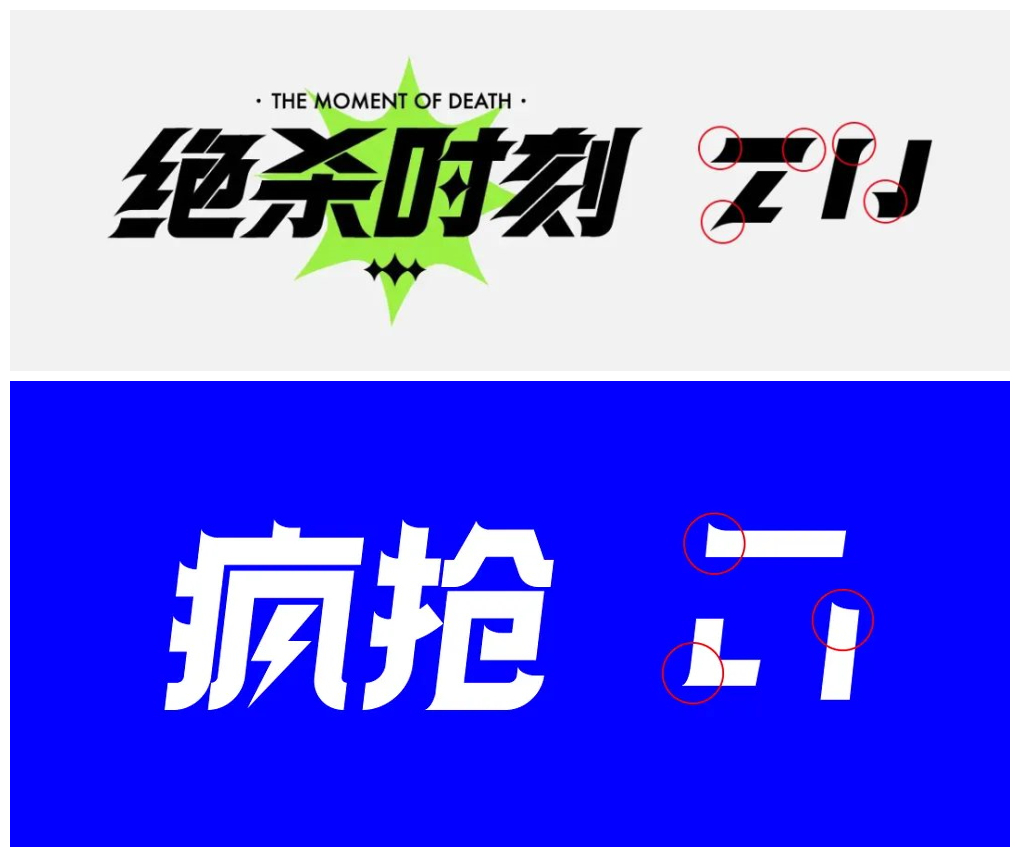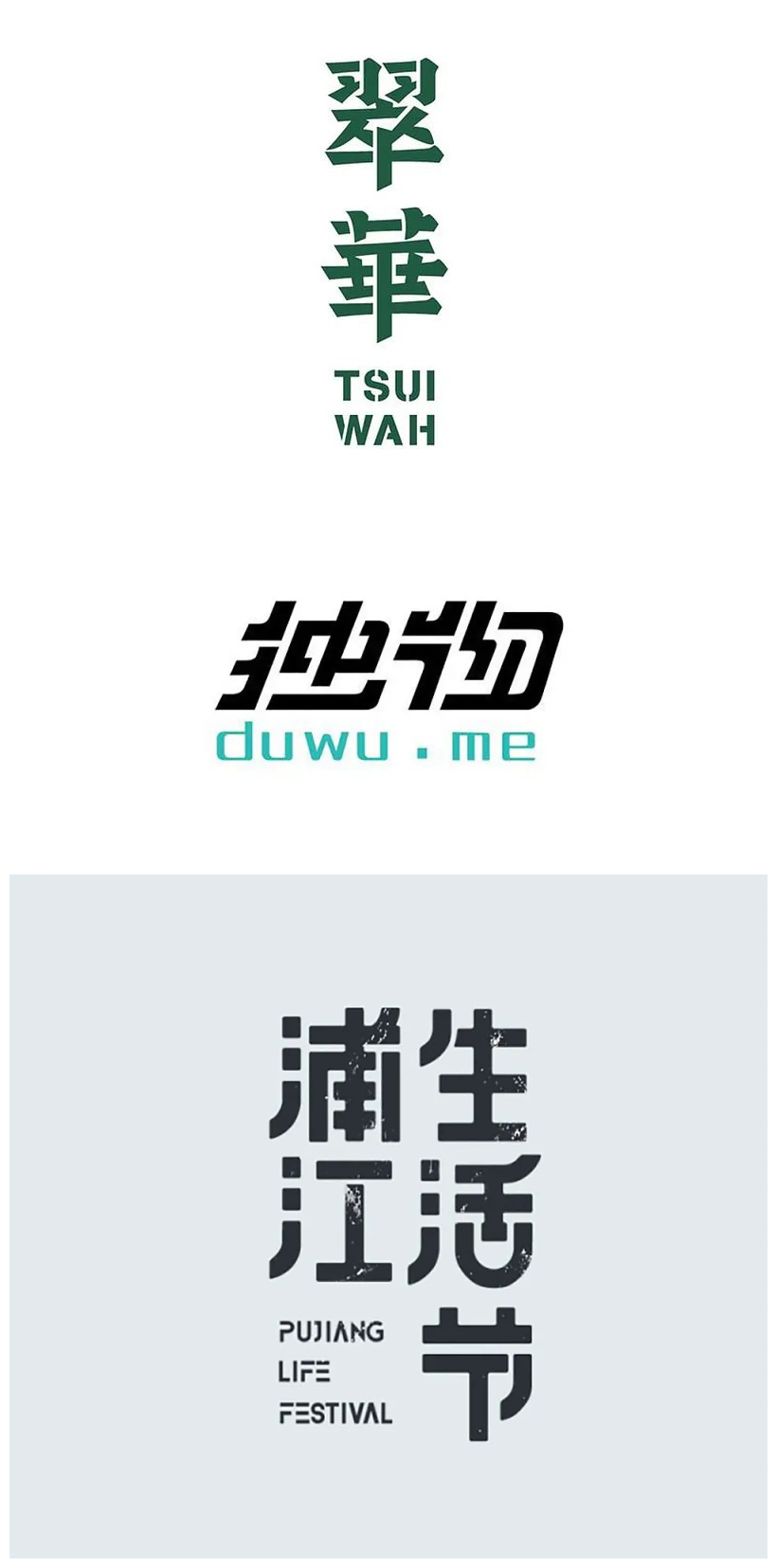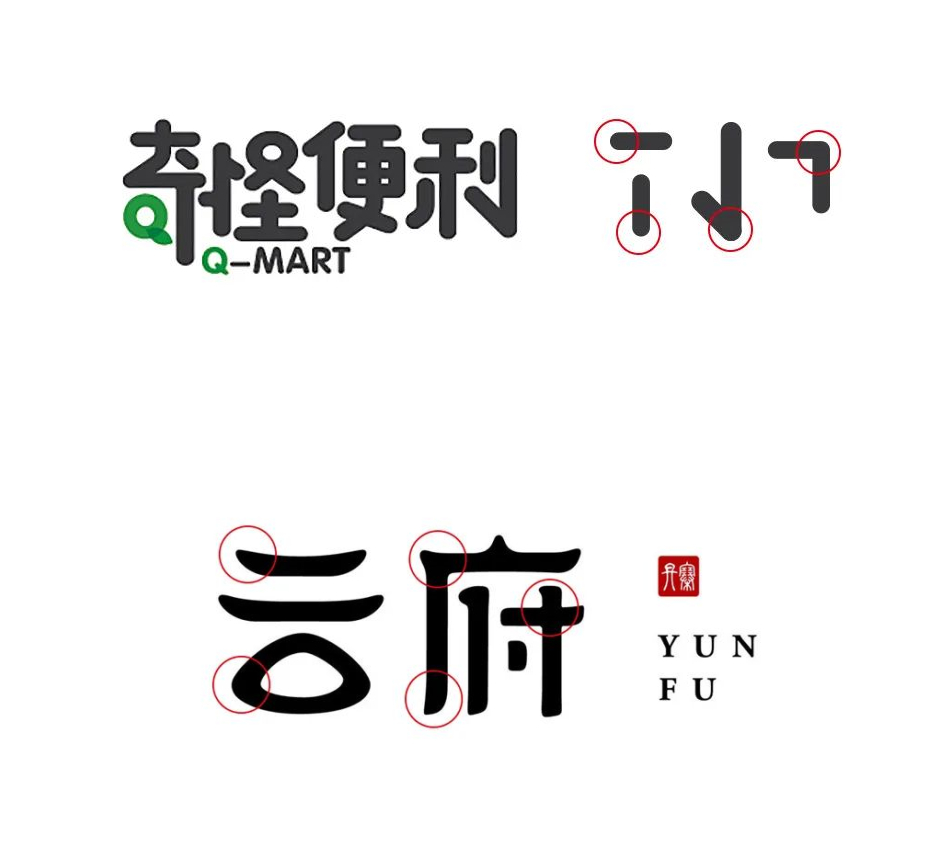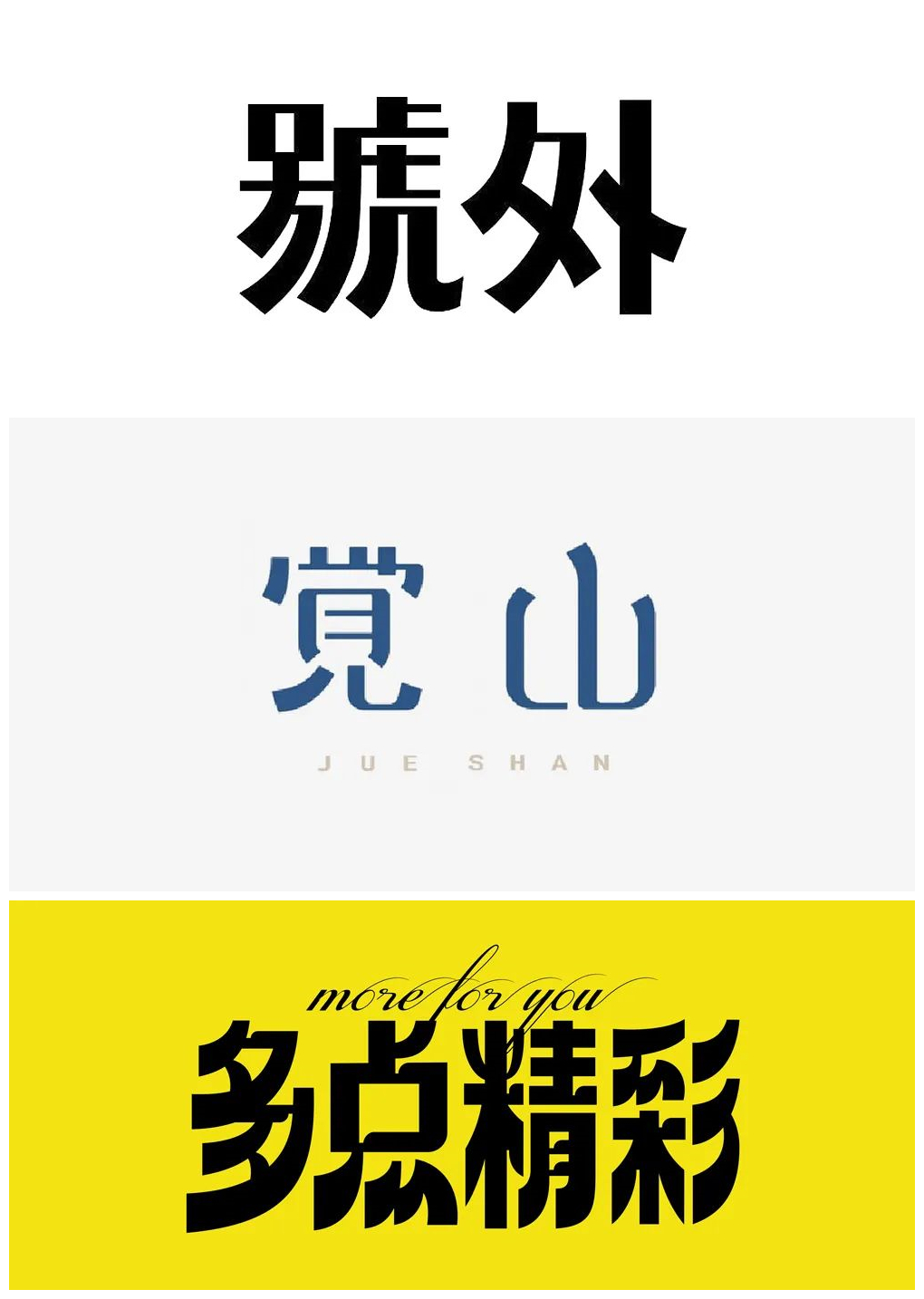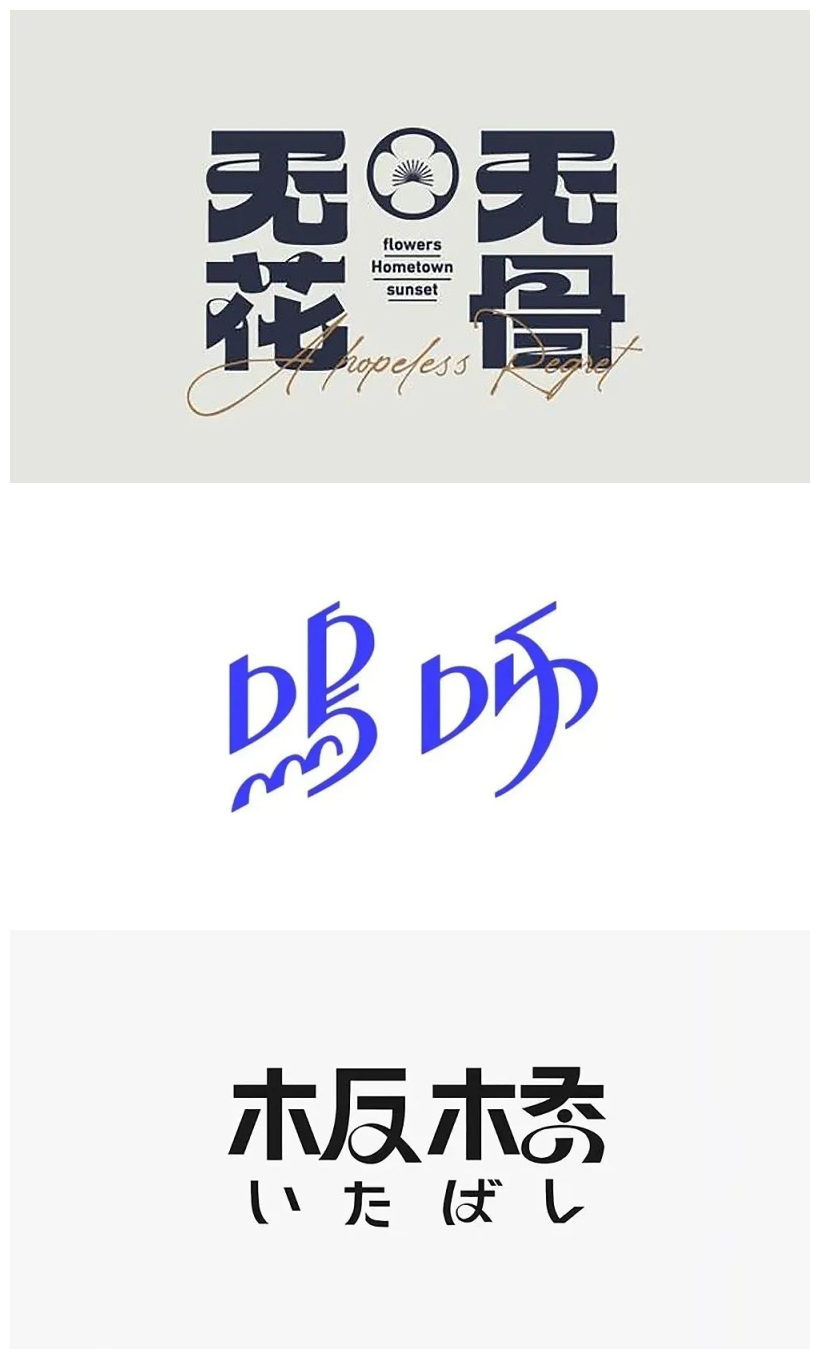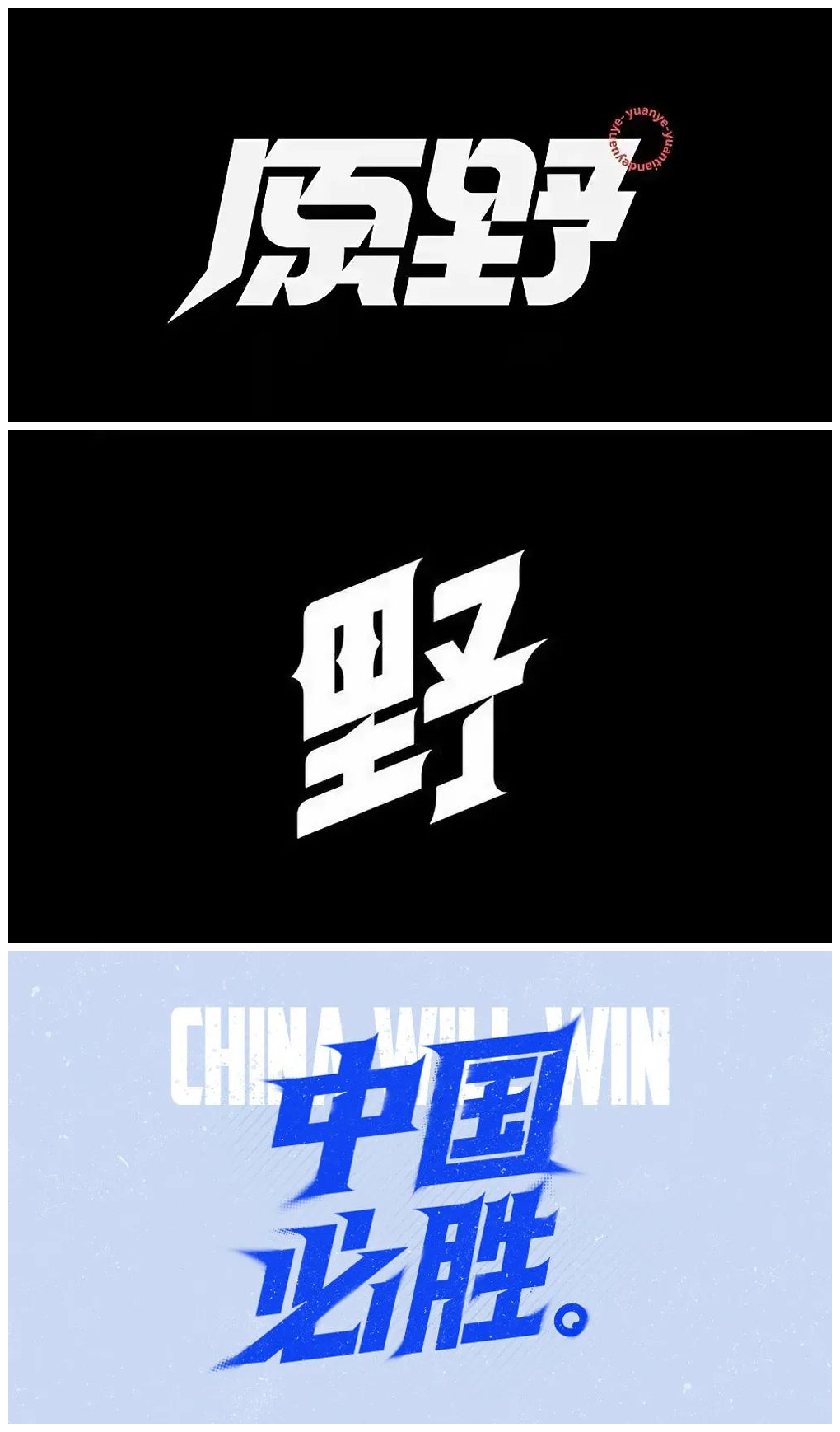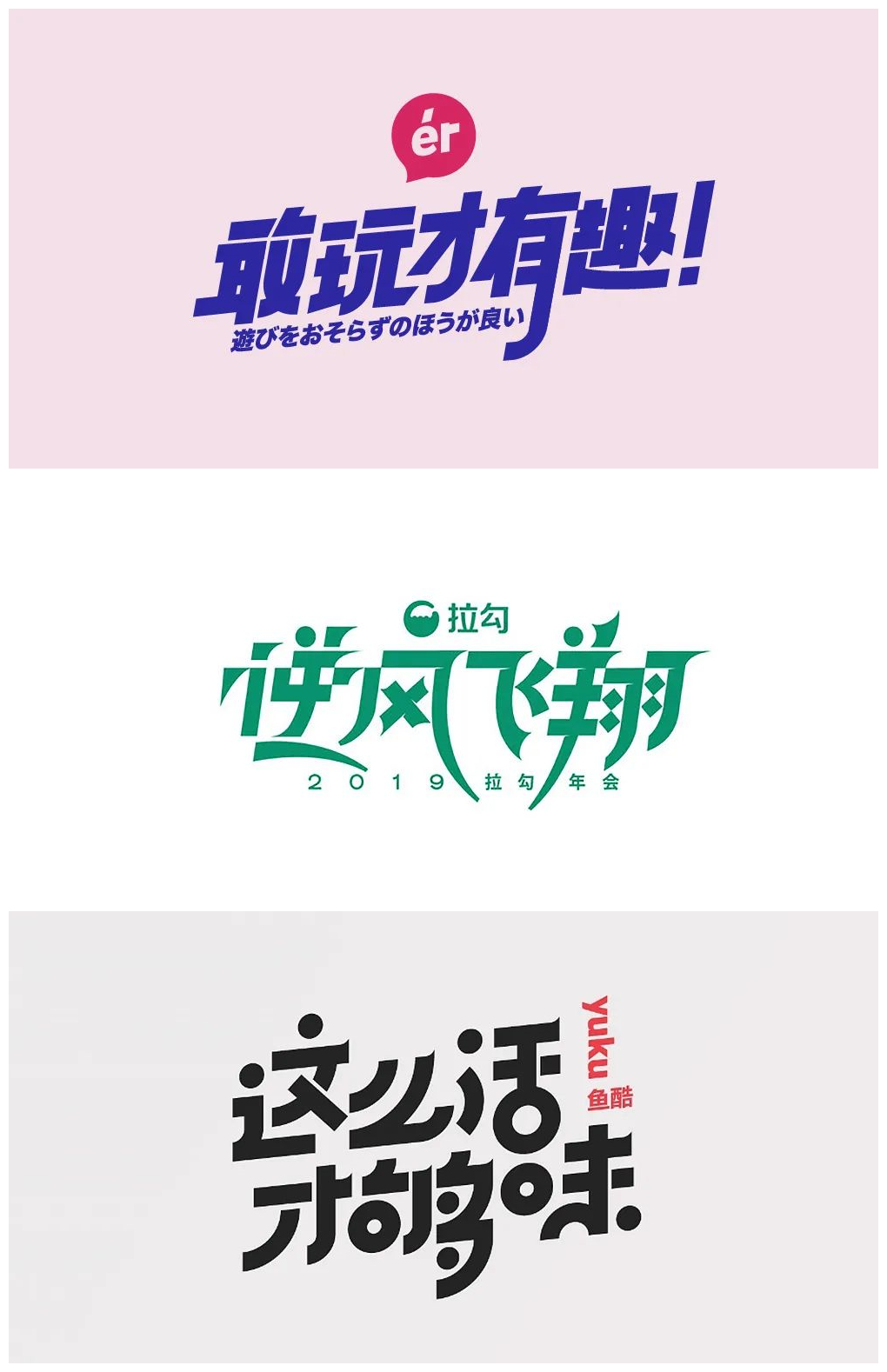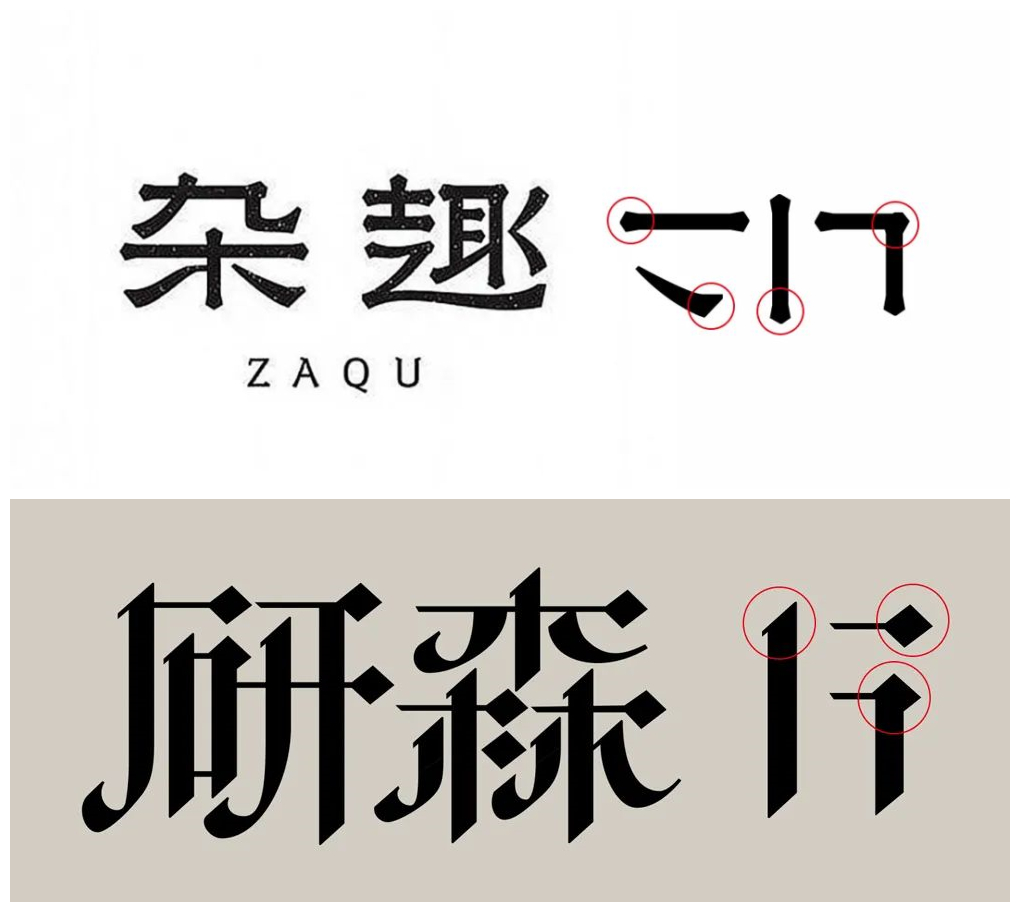
7个技巧让你的字体设计拉满细节感!
给笔画加衬线
相对而言,笔画有衬线的文字要比没有衬线的看起来更精致、更有细节,比如宋体与黑体的对比,衬线的种类非常多,可以根据不同字体的调性来进行设计。
上图的两种衬线比较适合一些笔画较粗、偏向强劲有力的字体。
上图的两种衬线则比较适合文雅一点的字体。
圆角处理
即把笔画的端点、笔画交叉处、转角等位置做成圆角,圆角比直角给人的感觉更精致,有被修饰过的感觉,当然,圆角并不适合所有字体。
当圆角比较大时,文字的调性会偏向于温和、可爱。
如果想要减少可爱的感觉,那么就把圆角尽量缩小或者把笔画做细一点。
把笔画交叉处断开
即在文字某些笔画交叉的地方,把其中的一个笔画裁掉一小段,使两个笔画从交叉变成分离的状态,这么处理可以使文字看起来更透气,也可以增加字体的设计感和细节。
在笔画交叉处切口
这种处理方式与上一条技巧类似,不同的是不需要把笔画完全切断,而是只开一道口子,而这道口子具体的形态也可以有很多种,当然,这也是由字体的笔画结构所决定的。
笔画别太整齐
有些设计师在排版和设计字体的时候都喜欢严格对齐处理,这样的版面和字体都容易显得太拘束、没有变化,所以,有时候刻意让文字的笔画不对齐,甚至把文字的排版也做错位处理,保持自然的感觉会更耐看。
连笔
连笔是手写字体惯用的方式,但也经常被设计师用到宋体和黑体的字体设计中来,把文字中的某些笔画做一些局部的连笔处理,可以适当中和某些字体给人过于刚硬的感觉,同时也给字体增添了一些细节。
笔画有粗细变化
通常来说非等线体比等线体设计起来会更加麻烦一点,所以很多设计师会习惯性把字体设计成等线体,而这类字体的笔画相对来说变化比较少,所以如果给笔画(通常是曲线笔画)做一点粗细变化,那么也可以让字体看起来更丰富。
结语
以上每个技巧并不具备普适性,而是适合某些特定调性的字体设计,并且往往是要综合起来使用,所以,我们要根据自己的实际需要来选择使用,另外,细节虽重要,但是字体本身的骨架和造型好看、字体调性符合设计需求才是关键,切勿本末倒置。